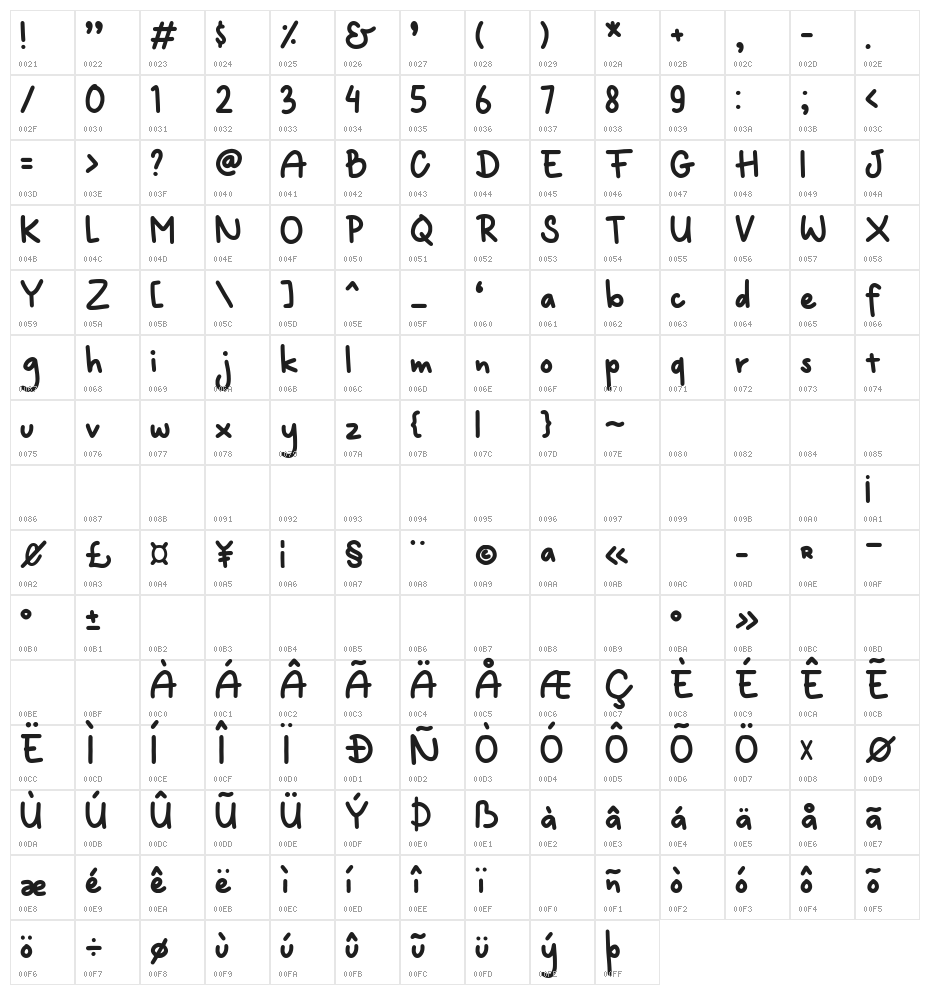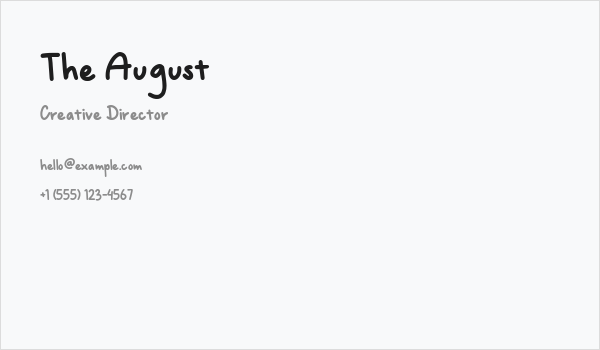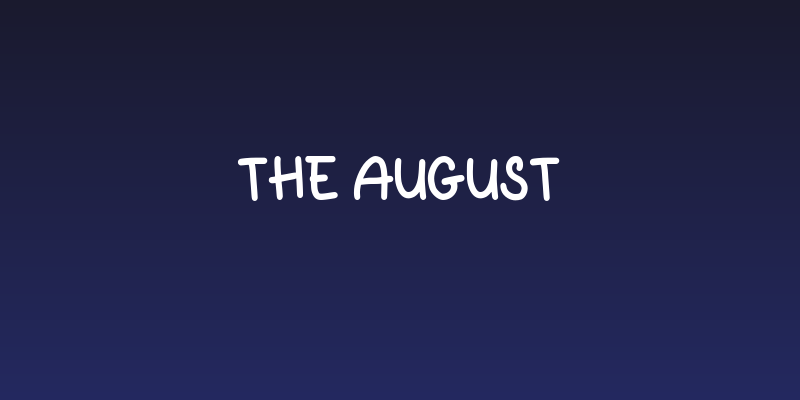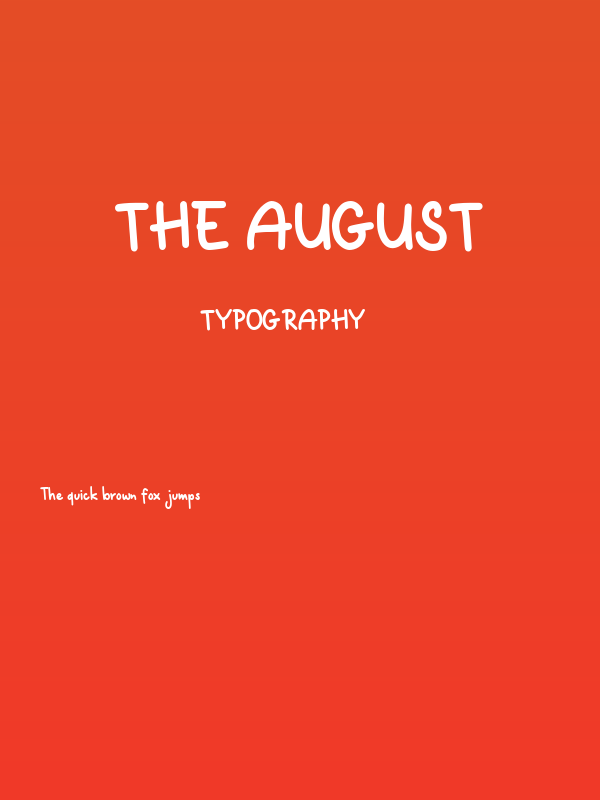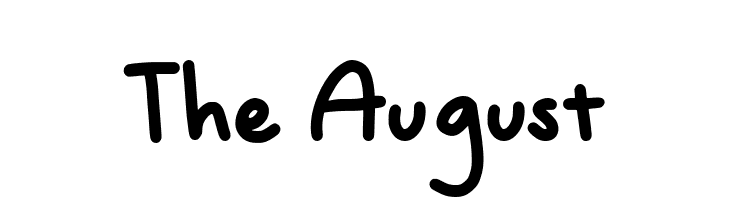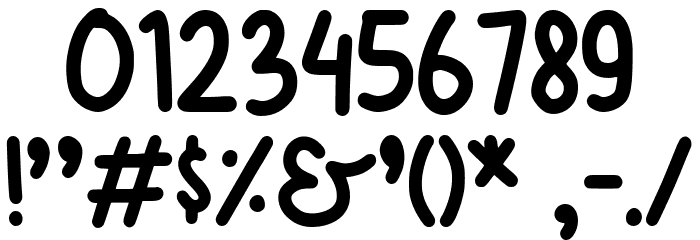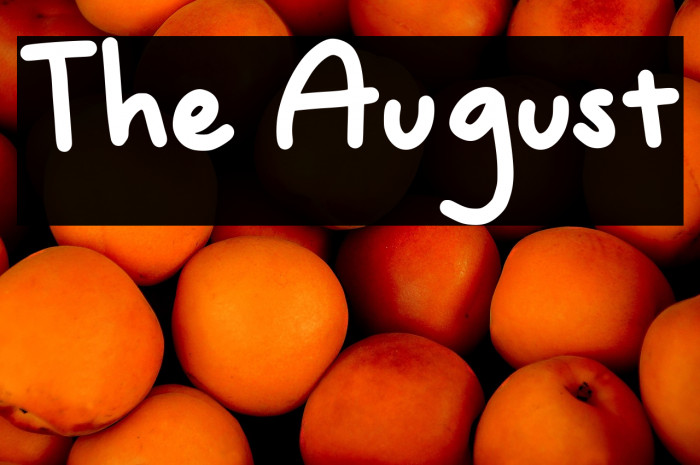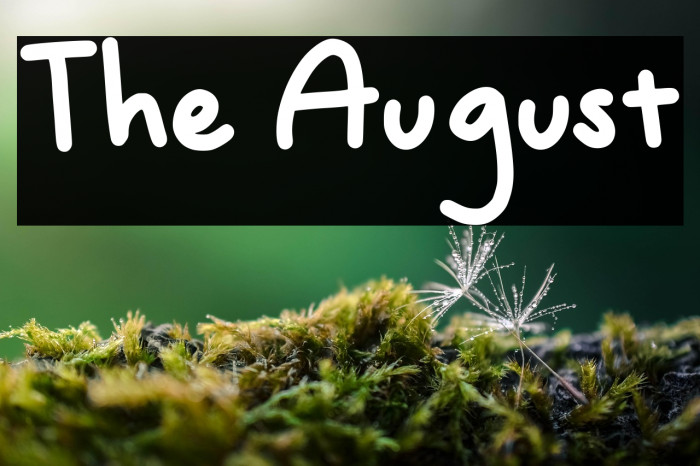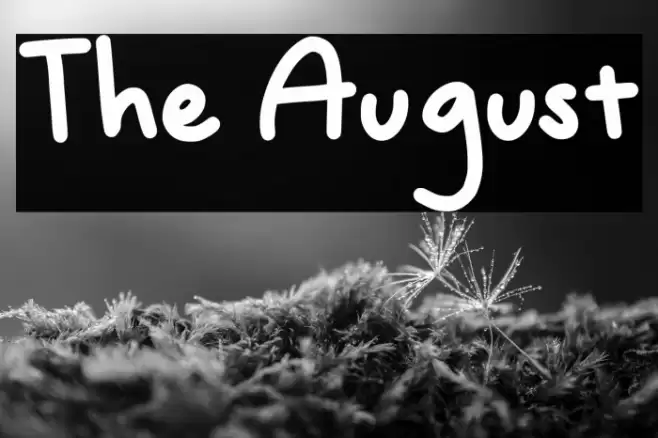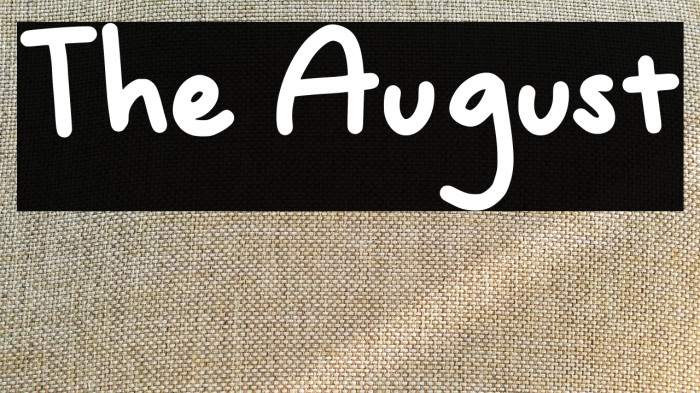
The August Font
| Gesamtstil | Casual, Playful |
| Anwendungsfall | Headlines, Logos, Informal Text |
| Vorgeschlagene Projekte | Ideal for invitations, greeting cards, children's book covers, and playful branding. |